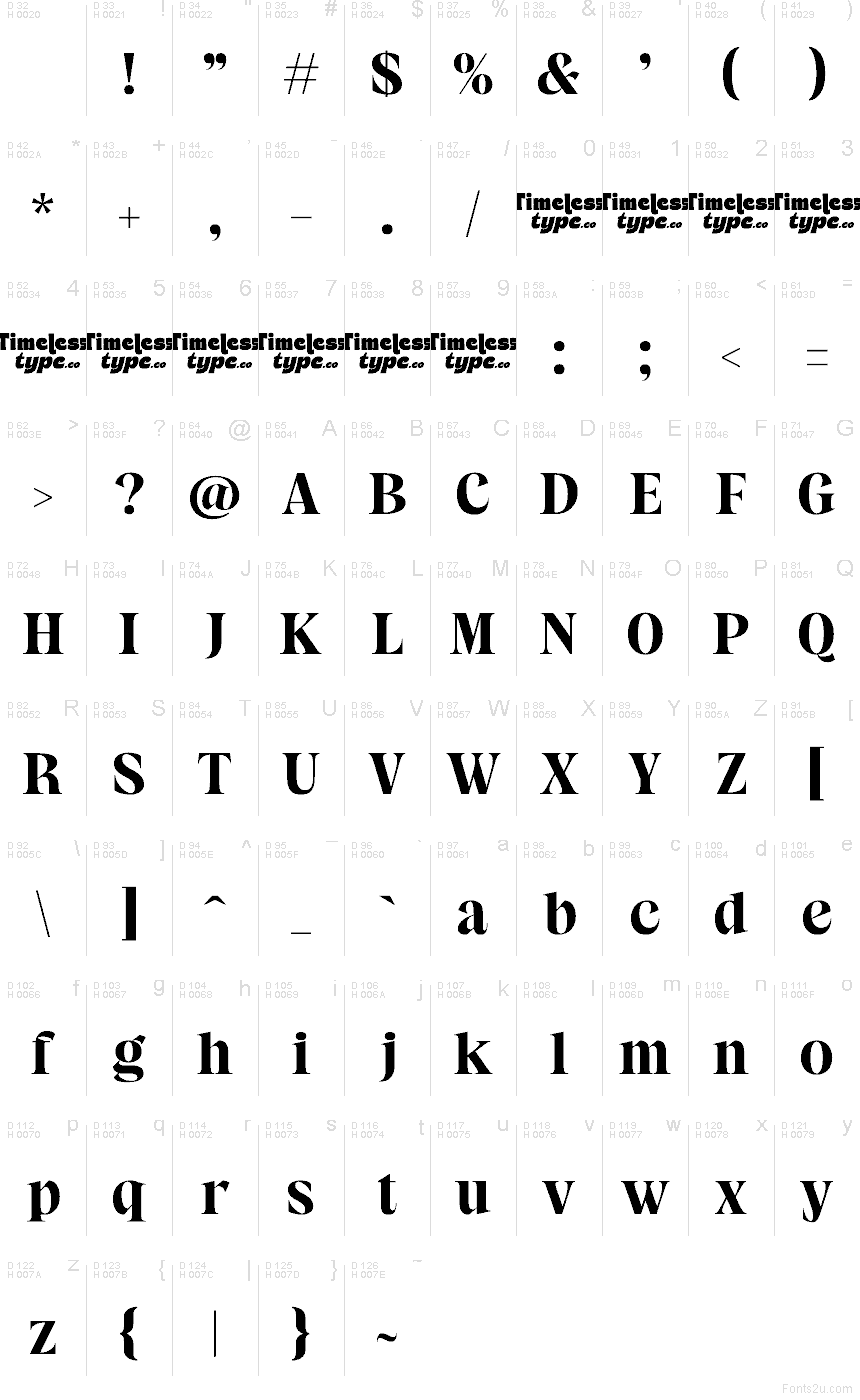
Verleihen Sie Ihrem Design-Portfolio mit der unverkennbar glamourösen Ausstrahlung von Sagira Beverly - Bold Tall Serif Font neue Strahlkraft. Diese Display-Schrift verbindet gekonnt markantes visuelles Gewicht mit einer eleganten, gestreckten Struktur zu einem dynamischen typografischen Statement. Ihre fließenden Kurven und scharfen Serifen erzeugen einen kontrastreichen Rhythmus – ideal, um in großformatigen Schlagzeilen und anspruchsvollen Branding-Projekten sofortige Aufmerksamkeit und natürliche Raffinesse zu erzielen.
Entfalten Sie unvergleichliche gestalterische Flexibilität durch vielseitige OpenType-Funktionen. Sagira Beverly - Bold Tall Serif Font bietet 29 sorgfältig gestaltete Ligaturen und 40 stilistische Alternativen, mit denen Designer individuelle typografische Kompositionen wie von Hand gezeichnet erstellen können. Dieser umfangreiche Zeichensatz sorgt zusammen mit zwei eigenständigen Schnitten (Regular and Italic) für einen harmonischen visuellen Fluss und macht die Schrift zur perfekten Wahl für anspruchsvolle Editorial-Layouts und unverwechselbare Luxusverpackungen.
Erweitern Sie die Reichweite Ihrer Marke, ohne Kompromisse bei der erlesenen Ästhetik einzugehen. Dank der umfassenden Sprachunterstützung passt sich Sagira Beverly - Bold Tall Serif Font reibungslos an globale Märkte an und zeigt sich bei internationalen Projekten bemerkenswert vielseitig. Diese weltweite Kompatibilität stellt sicher, dass Ihre hochwertige Designvision unabhängig von Sprache und Region optimal zur Geltung kommt, die Markenidentität weltweit gewahrt bleibt und neue Kundengruppen erschlossen werden.
Speziell für das High-End-Segment entwickelt, ist Sagira Beverly - Bold Tall Serif Font das ultimative Werkzeug für anspruchsvolle Marken. Die Schrift eignet sich hervorragend für Luxus-Branding, exklusive Magazintitel, High-Fashion-Editorials, opulente Kosmetikverpackungen und wirkungsstarke Social-Media-Kampagnen. Heben Sie Ihr Projekt mit dieser zeitlosen und zugleich kühn modernen Serifenschrift auf ein neues Niveau und verleihen Sie Ihrer Arbeit erstklassige Qualität und unbestreitbaren Stil.